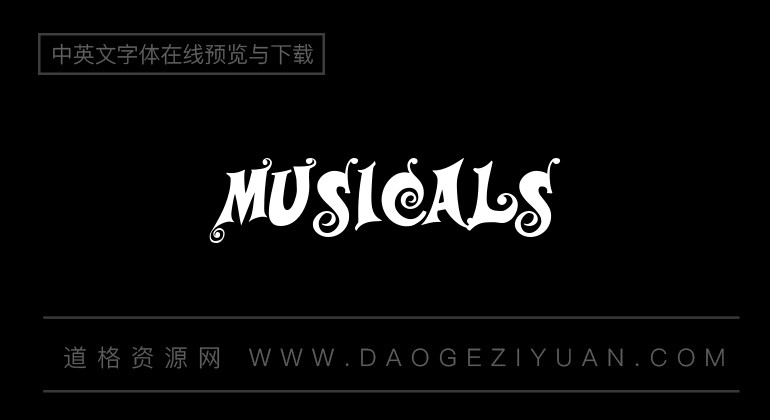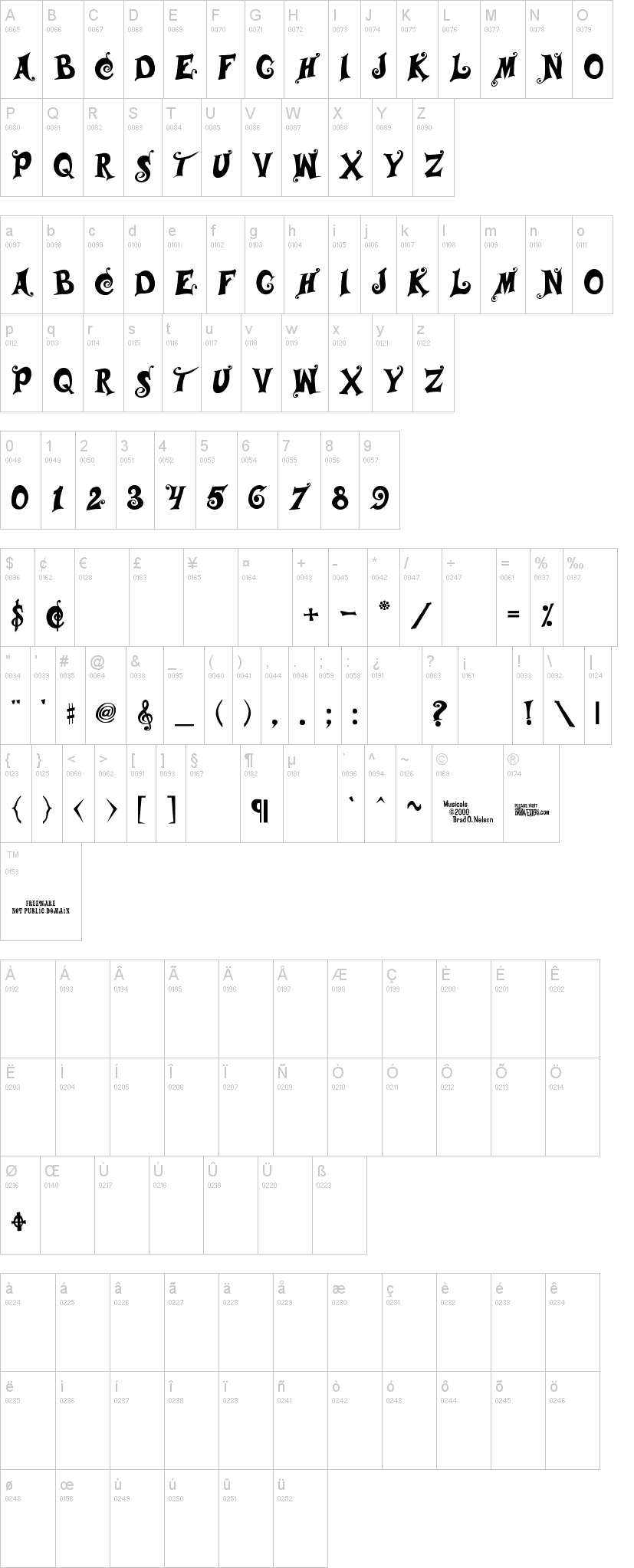
Musicals
Musicals 字体是一种具有艺术感和戏剧性的字体,它的设计灵感来源于音乐剧和舞台剧的海报和宣传材料。这种字体通常具有粗大、华丽、动感的特点,字母之间也会有比较大的间距,以增强视觉效果和视觉冲击力。Musicals 字体通常被用于音乐剧、戏剧和电影的海报、宣传册、宣传广告和演员或演出者的名字。
Musicals是一款非常不错的手写艺术字体,具有很好的视觉感,适合于文化类的宣传设计、商业类品牌的广告和产品包装设计以及个性化文字排版等较多场景。